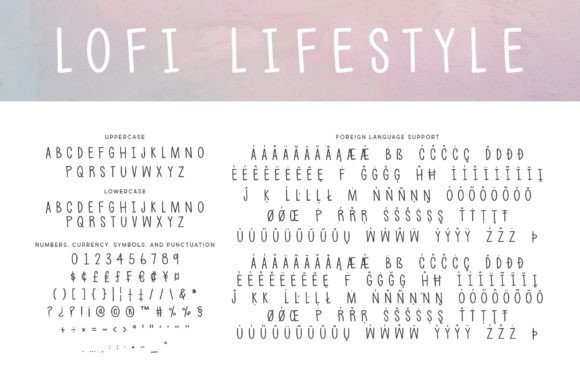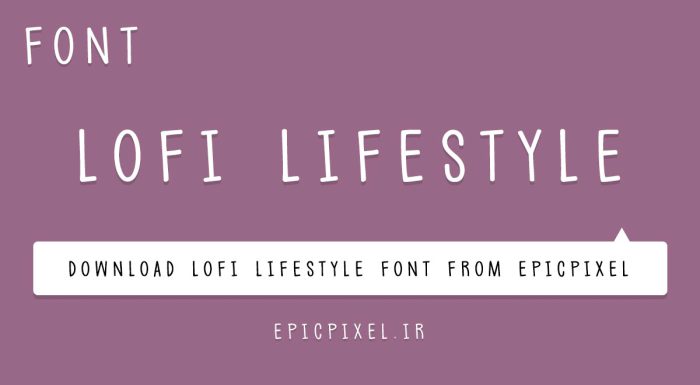
فونت Lofi Lifestyle انگلیسی
| ⭐ توضیحات | Lofi Lifestyle Font یک تایپ سرد، دستنویس و تمام حروف است که در سال 2022 توسط Brittney Murphy Design ایجاد شد.
با بیش از 330 علامت، فونت LoFi Lifestyle از اکثر زبان های مبتنی بر لاتین پشتیبانی می کند و نسخه کامل شامل اعداد و علائم نگارشی است که شما نیاز دارید. استفاده از ستاره (*) به شما یک نماد هدفون سرگرم کننده می دهد که می توانید در پروژه های خود از آن استفاده کنید. |